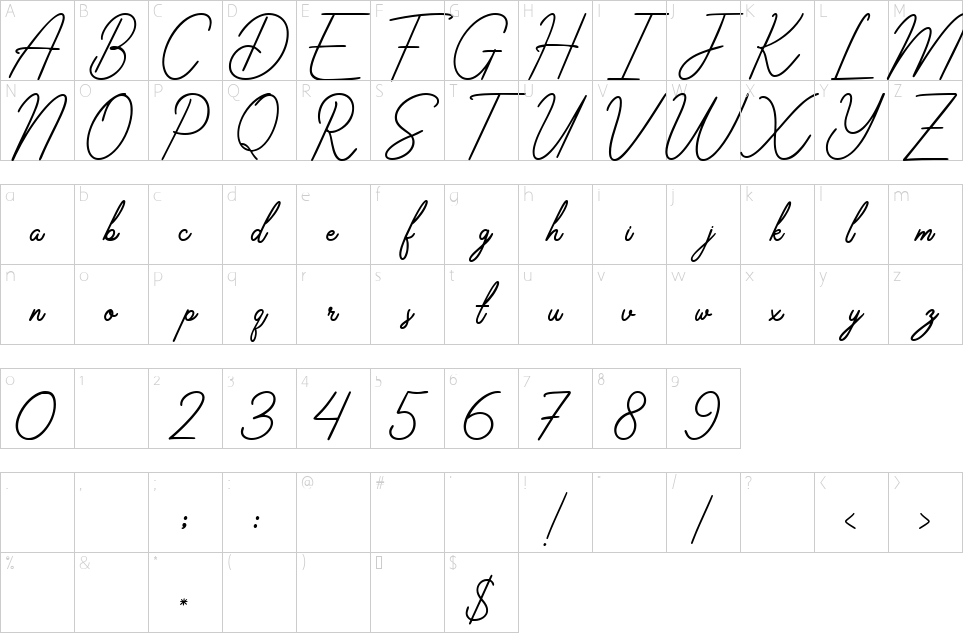
A fonte Antoinette Miller é um gráfico elegante e sofisticado, ideal para criações digitais de alto padrão. Desenhada pelo talentoso equipe da dealitastudio, essa fonte foi popular entre designers e usuários. Antoinette Miller foi baixada mais de 3,500 vezes, evidenciando seu valor e beleza. Seja para escrita editorial, design gráfico, logotipos ou qualquer outro tipo de projeto, Antoinette Miller oferece um estilo único e versátil. Ela combina com facilidade em ambientes digitais modernos e moderniza qualquer projeto de um clique. Se você está procurando por uma fonte de qualidade com estilo, Antoinette Miller pode ser a escolha perfeita para seu próximo projeto.